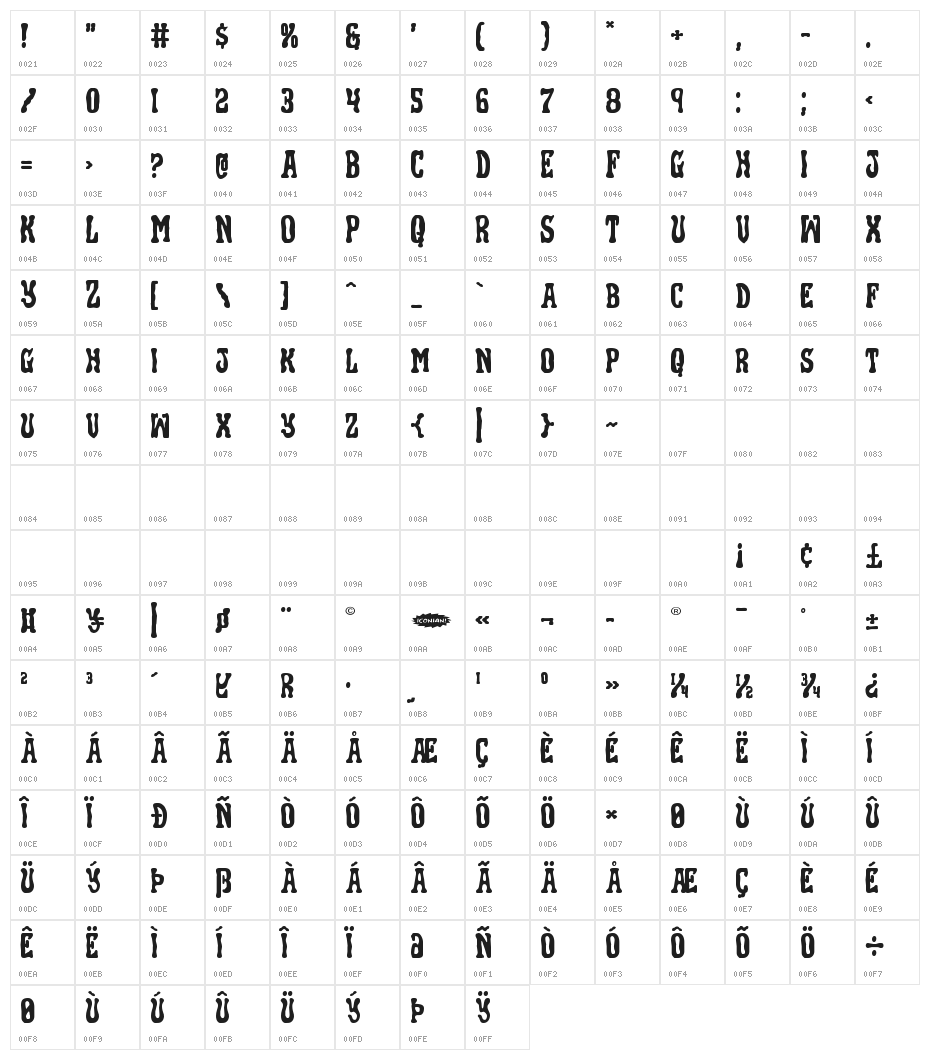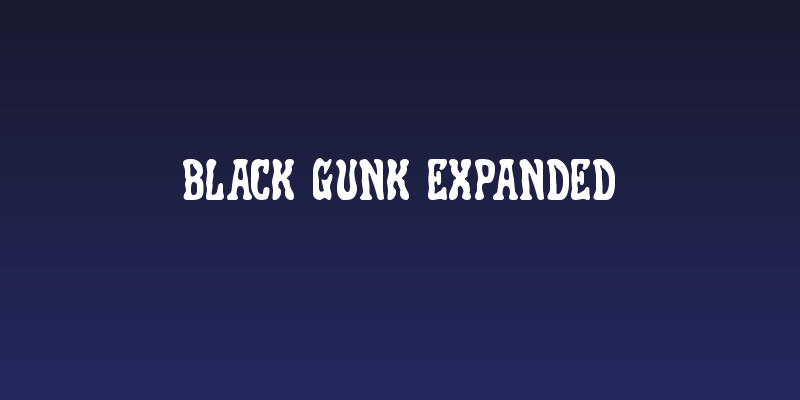
Black Gunk Expanded Font
| Progetti proposti | Ideal for posters, album covers, branding for creative industries, and any project needing a bold, unconventional typeface. |